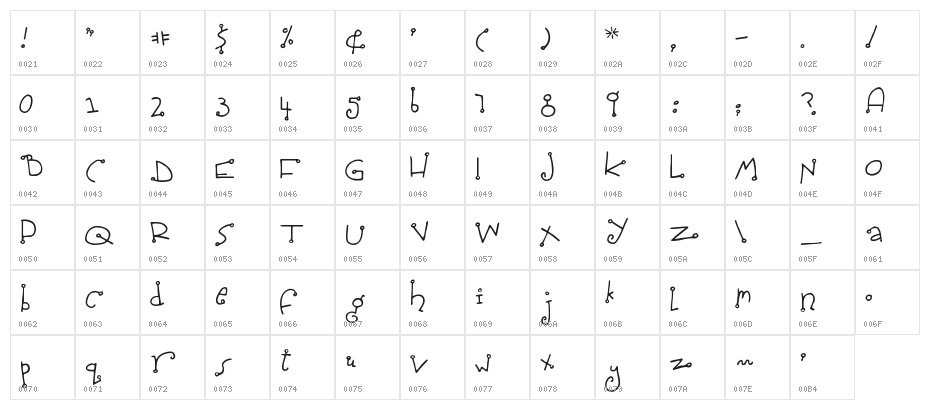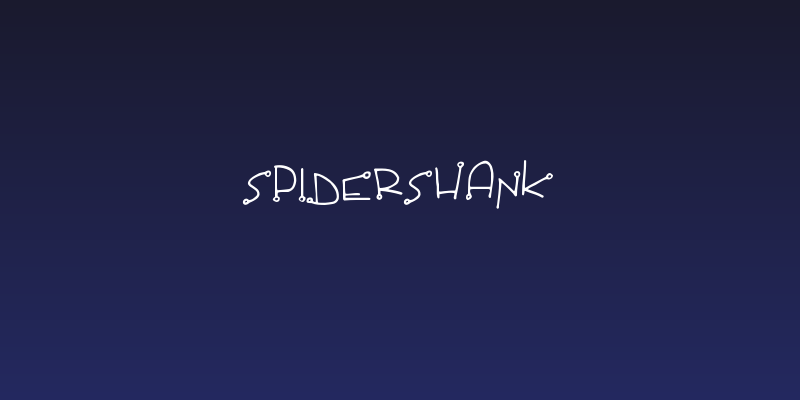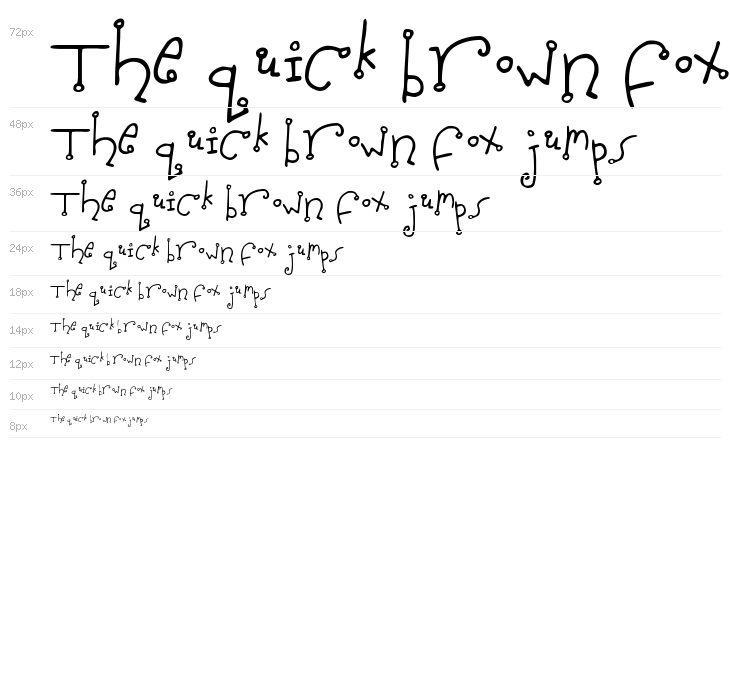
Spidershank Font
| Stile generale | Whimsical, Playful |
| Caso d'uso | Logos, Posters, Creative Projects |
| Progetti proposti | Ideal for children's books, playful branding, greeting cards, and creative posters. |